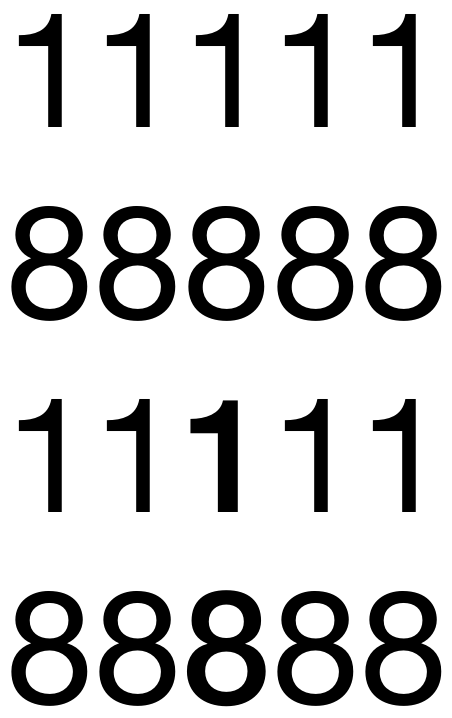
Hat die Neue Helvetica keine Proportionalziffern?
Ich habe neulich ein paar Tests gemacht in XeLaTeX (angehängter Screenshot) und mir ist bei der Neuen Helvetica aufgefallen, dass Proportionalziffern fehlen, man sieht keine Änderung nach dem Umstellen im Code. Ist das richtig so? Auch beim fontshop sieht man, dass die Proportionalziffern exakt so wie die Tabellenziffern aussehen: https://www.fontshop.com/families/neue-helvetica
Ich fände das ziemich komisch, eine Schriftfamilie von so einem Kaliber so mager auszustatten. Ich müsste jede "1" manuell kernen, damit was anständiges rauskommt in jeder Anwendung außer in Tabellen. Weiß jemand, warum die die Schrift nicht besser ausstatten?
Ich kann dir zur Helvetica nix, sagen, weiß dafür aber dass XeTeX die Definition eigener Kerning-Klassen erlaubt, dann müsstest du zumindest nicht jede Eins von Hand ausgleichen ;-) meld dich, wenn du mehr Infos dazu brauchst …